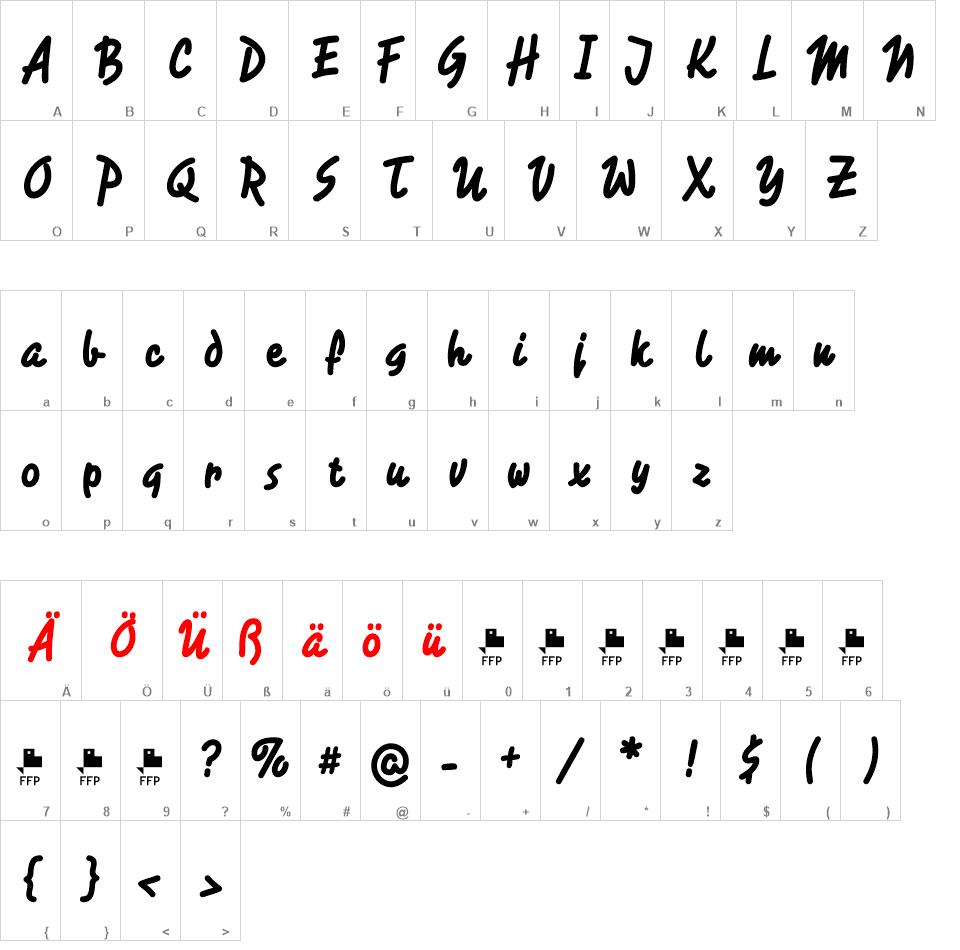
Rotulona Hand
Rotulona Hand ist eine dicke handschriftliche Typografie mit fetter Kugelschreiber, hat ein fröhliches und sorgloses Aussehen ist perfekt für Grafik-Design und Werbung.